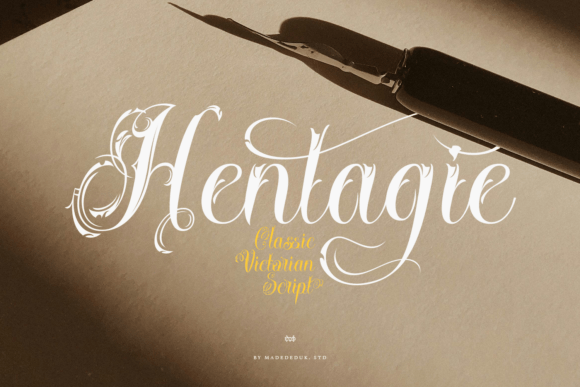
Hentagie
Het vinden van de juiste ontwerpelementen kan lastig zijn, maar Hentagie biedt een uitzonderlijke collectie die uw werk direct naar een hoger niveau tilt.
Of u nu POD-producten (Print on Demand), huwelijksuitnodigingen of afbeeldingen voor sociale media maakt, Hentagie is een ideale keuze.